“Félicitations! Vous avez atteint la fin du cours. Merci encore de m'avoir rejoint dans cette aventure créative; J'espère que vous vous sentez inspiré pour créer des affiches qui transmettent votre voix avec des messages puissants. Avant de vous dire au revoir, j'aimerais faire un petit résumé des étapes que je vous propose de suivre pour réaliser votre projet final. Choisissez votre thème et choisissez votre message. Ensuite, gribouillez vos idées et choisissez votre préférée. Ensuite, dessinez au crayon, photographiez votre croquis et transférez-le sur Illustrator. Jouez avec la composition et la couleur jusqu'à ce que vous soyez heureux.
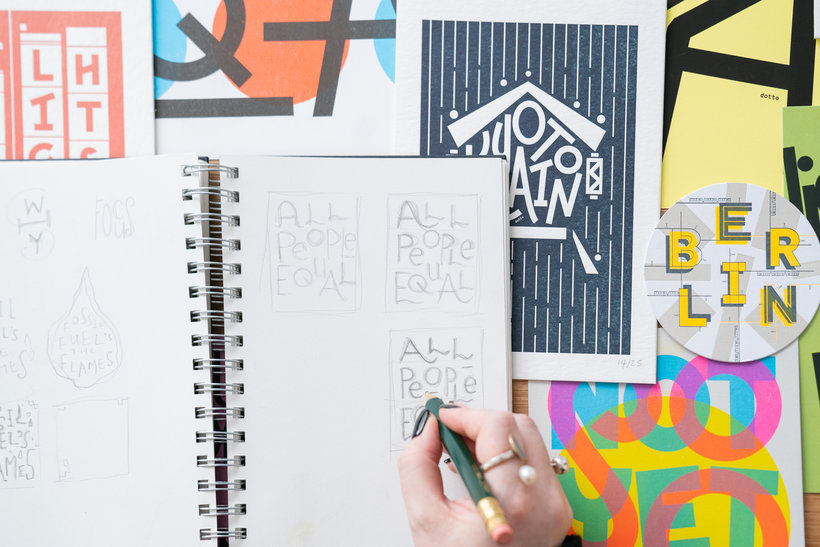
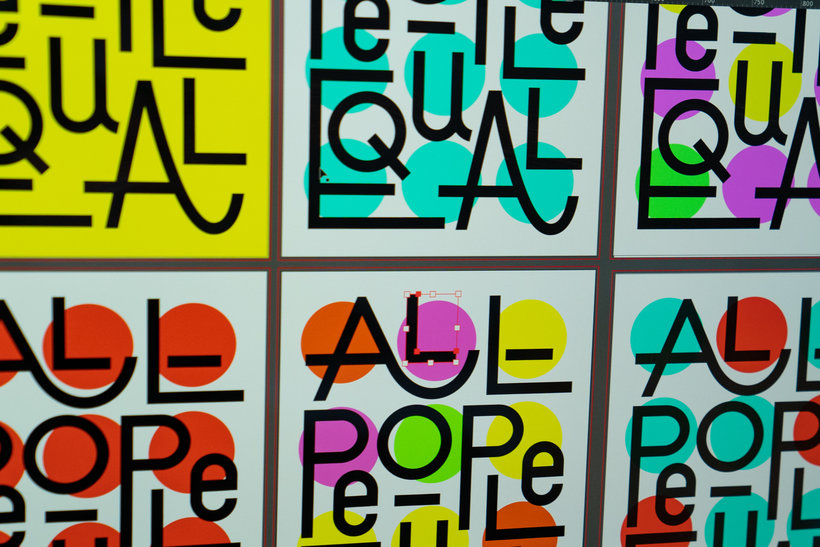
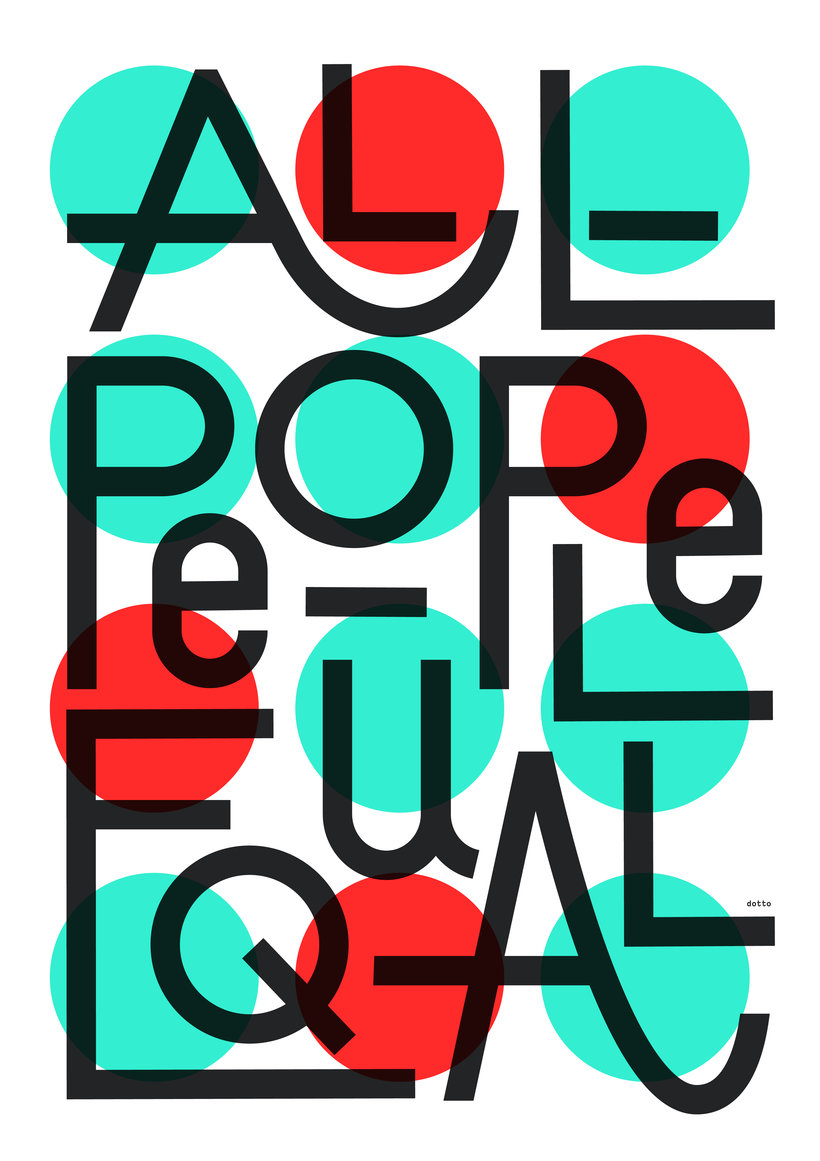
“Projet final Merci d'avoir suivi le cours, c'était cool de le faire pour vous. J'espère que vous l'avez vraiment apprécié. Comme nous en avons discuté, le projet final consiste à créer une affiche typographique avec un message qui signifie quelque chose pour vous. Nous avons commencé par rechercher comment le type peut créer une humeur et une sensation. Ensuite, nous avons examiné comment nous pouvons créer des messages et styliser nos compositions. Nous sommes ensuite passés à Illustrator et je vous ai montré comment mettre en place un espace de travail. Je vous ai montré comment nous pouv...”